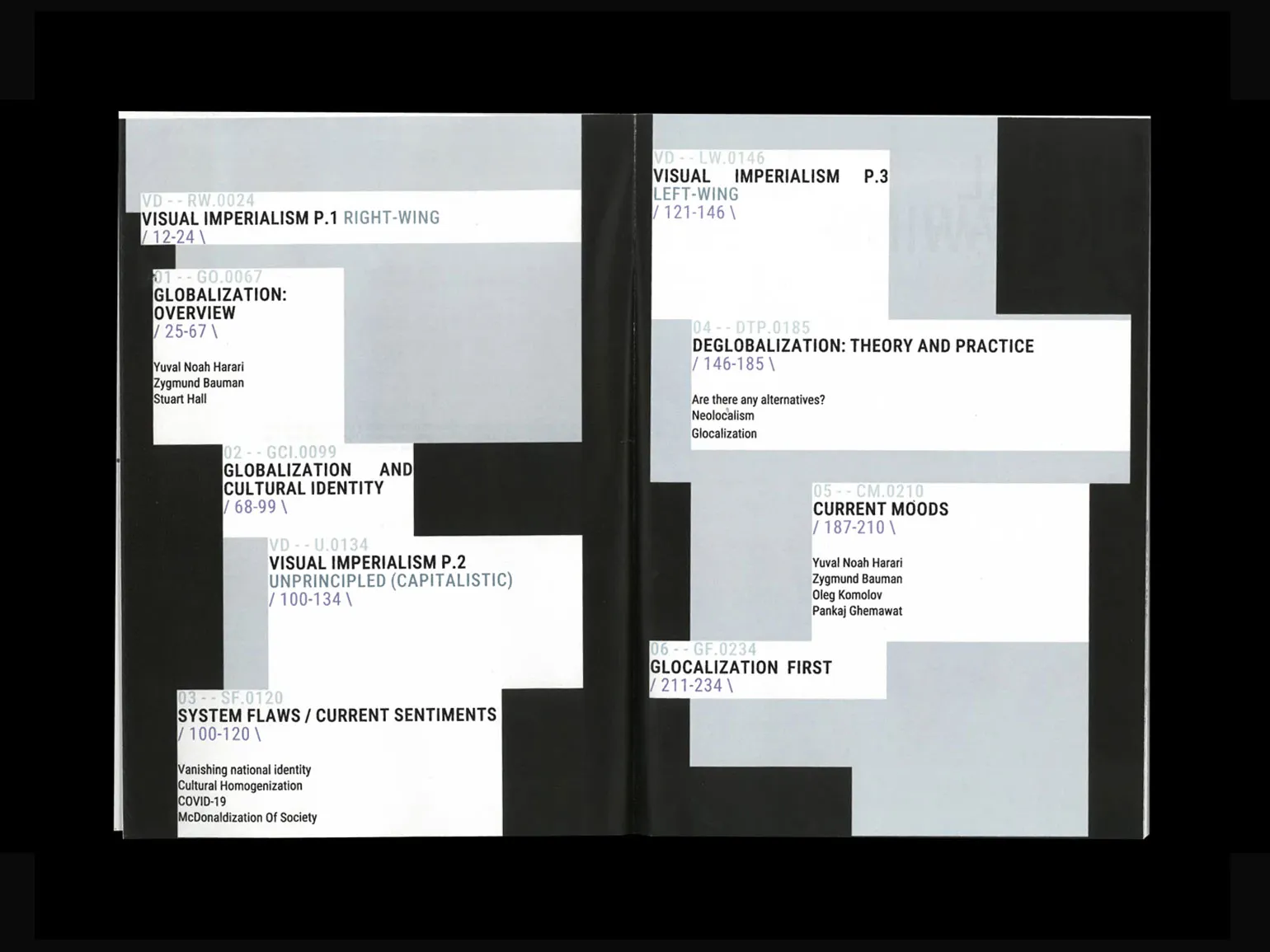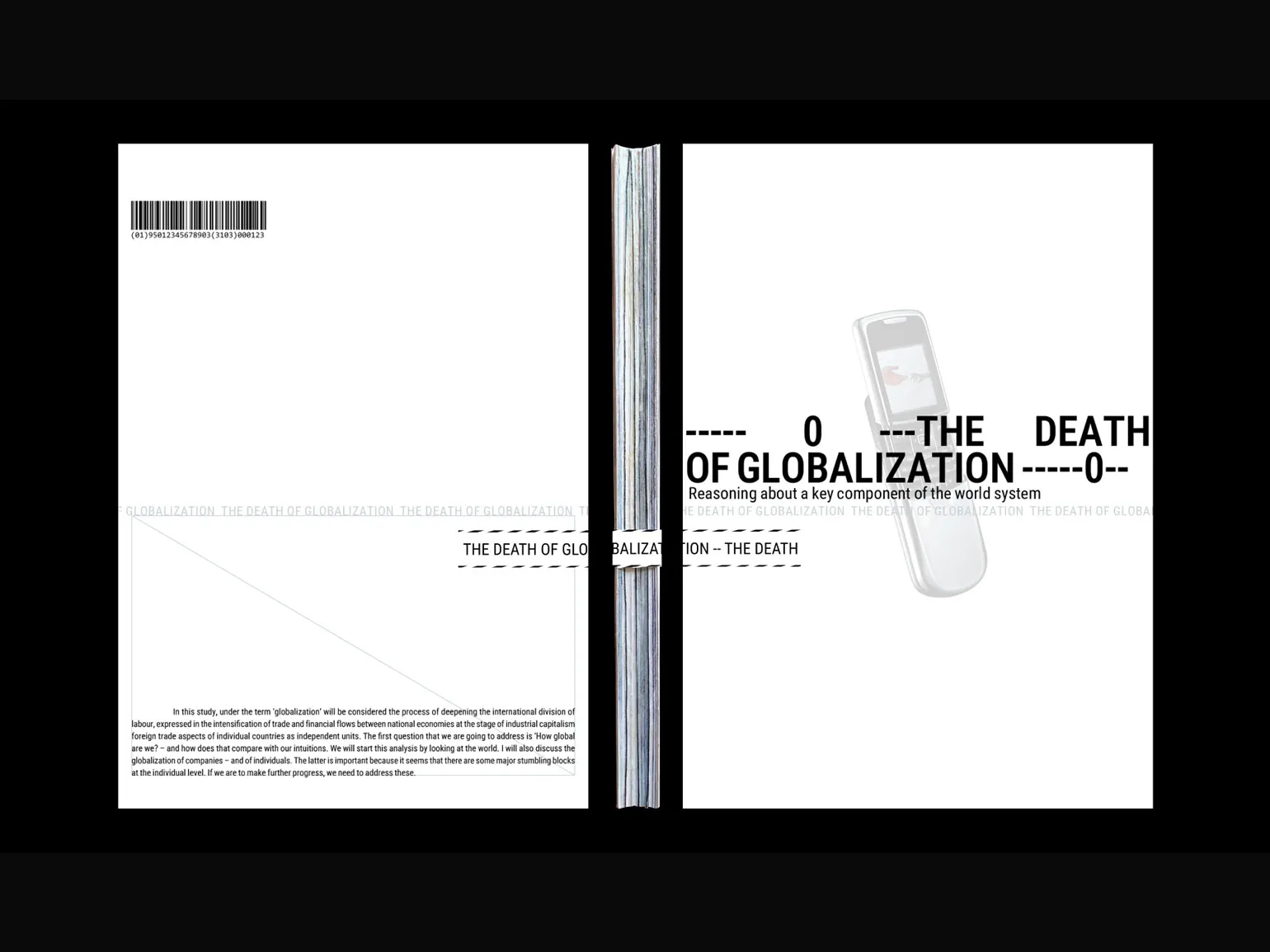
Сайт-портфолио режиссёра от студии naau
Дизайн-студия naau сделала сайт для режиссёра Сергея Рамза. Он снимает кино и рекламные ролики, занимается фотографией — в портфолио важно было показать его работы и нескучно, и удобно для зрителя в вебе, и привлекательно для будущих заказчиков.
Мы сделали уже очень много сайтов-портфолио для креативных индустрий, поэтому каждый следующий проект для нас — это вызов: мы не имеем права повторяться и должны каждый раз придумывать что-то новое, но учитывать специфику сферы. Нужно максимально погрузиться в контекст, чтобы найти метафору, особый стиль, продумать особенности вёрстки сайта и подачи информации для каждого случая.
Когда мы искали интересные решения для этого проекта, поняли, что эффект блюра для текста, изображений и видео позволит добавить в него необходимую степень аутентичности и органично соединить функциональность с метафорой этого приёма — отсылкой к наведению резкости объектива камеры. Сергей Рамз не только режиссёр и сценарист, но также и фотограф, поэтому идея ему сразу зашла, и мы постарались выкрутить её на максимум.
Одной из самых главных и сложных задач проекта было придумать и реализовать некую необычную вёрстку, чтобы сайт не был похож на множество других сайтов режиссёров. То, что получилось, радует: главная страница выполнена в формате одного экрана. Здесь, помимо метафоры с размытием и фокусировкой, мы также реализовали интересную навигацию между разделами, которая «повторяет» форму киноплёнки, где каждый раздел встроен в свой кадр: если навести на него, можно посмотреть небольшое видеопревью.
Сергей Казанков, веб-дизайнер
Книга The Death of Globalization Анастасии Павловой
«Смерть глобализации» — выпускная работа студентки ШД НИУ ВШЭ. Это многостраничное издание на тему мегасистем производства, распределения товаров, социальных и политических процессов, которые делают мир единообразным, но не единым.
Это единственный мой проект, в котором я сразу обнаружила нужный образ — грузовой контейнер — и не искала других вариантов. Обычно их очень много, и мне нужно время, чтобы проверить все на практике. Всё началось с исследования темы, в ходе которого я узнала, что изобретение грузового контейнера стало бустером в развитии глобализации. Я давно уже подмечала типографику на контейнерах рядом с домом, так что картинка сложилась очень быстро.
Я видела вёрстку сдержанной, холодной, похожей на конструктор Lego. Глобализация в целом всё унифицирует: стирает уникальность, самобытность. Производство бесчисленных товаров, которые потом потребляются во всех странах. К слову, сами грузовые контейнеры соответствуют единым стандартам по всему миру и складываются по блочному принципу. То есть контейнер из Японии легко подойдёт к контейнеру из Латинской Америки.
Во всей книге тексты набраны Roboto Condensed. Мне хотелось взять зауженный гротеск, отсылающий к технической маркировке на контейнерах, и при этом избежать моноширинных шрифтов, у которых весьма выразительный характер. Нужно было найти достаточно нейтральный шрифт с техническим оттенком.
Меня радует, что в этой книге получился единый слаженный образ, в котором нет для меня чужеродных элементов. Иногда хочется в дизайне использовать сразу несколько полюбившихся приёмов, но они оказываются из разных жанров и не работают друг с другом. Мне очень полюбилась бегущая строка с колонтитулами и колонцифра внутри технического треугольника. А в ресёрче больше всего удивила история про резиновых уточек, которые в 1990-х во время перевозки в огромных контейнерах попали в шторм и отправились в плавание по всему миру 🙂
Это магистерская работа, и, по сути, здесь мало отличий от бакалавриата. Ты так же сам придумываешь контент, можешь, если что, выкинуть некрасивую фотографию или лишний текст. В коммерческой работе убрать что-то неугодное получается редко.
Два года назад во время работы над первым дипломом я несильно думала о том, насколько мой дизайн будет жизнеспособным в реальном мире. У меня была задача сделать что-то невероятно дизайнерское — заявить о себе, скажем так. К концу магистратуры мой фокус сместился на поиск более собранных лаконичных образов, которые будут понятны людям, далёким от дизайна. Поиск баланса между интересным дизайном и дизайном хоть немного понятным — сложная задача, которую я ставлю перед собой сейчас.